5 Cách chọn Font chữ cho bộ nhận dạng thương hiệu
Trong lĩnh vực thiết kế bộ nhận dạng thương hiệu, một thương hiệu mạnh được tạo thành từ một ý tưởng hoàn hảo, một biểu tượng đặc trưng và một Font phù hợp. Ở đây, chúng ta sẽ bàn về Font chữ.
1.Dễ đọc
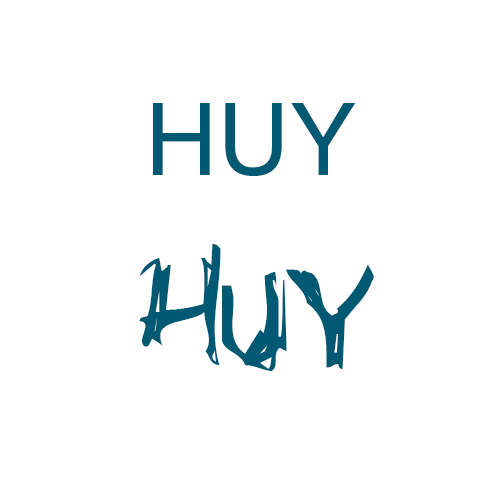
Khi bạn tạo ra một Logo hay một sản phẩm thiết kế nhận dạng thương hiệu, bạn thấy nó đẹp và sáng tạo nhưng người xem thì không thấy như vậy do nó quá phức tạp. Nói tóm lại, bạn phải chọn Font chữ thật đơn giản, dễ đọc. Nếu bạn chọn những Font chữ uốn lượn, rườm rà thì sẽ gây khó chịu cho người xem.
Bạn phải làm sao cho người xem có thể nắm được tên, màu sắc và cảm nhận được thông điệp ngay từ lần đầu nhìn vào Logo của bạn. Bạn nên chú ý về Font và cỡ chữ. Nếu như có thể bạn hãy đều chỉnh hệ chữ Bold, Regular, Light tùy ý để tạo sự sống động mà không gây khó nhìn cho người xem.
2.Khoảng cách từ và chữ
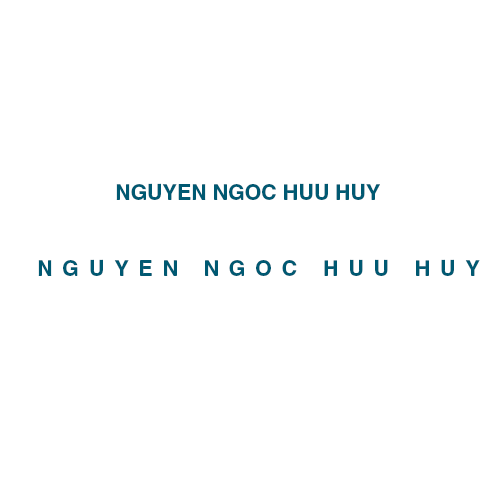
3.Phù hợp với không gian xuất hiện
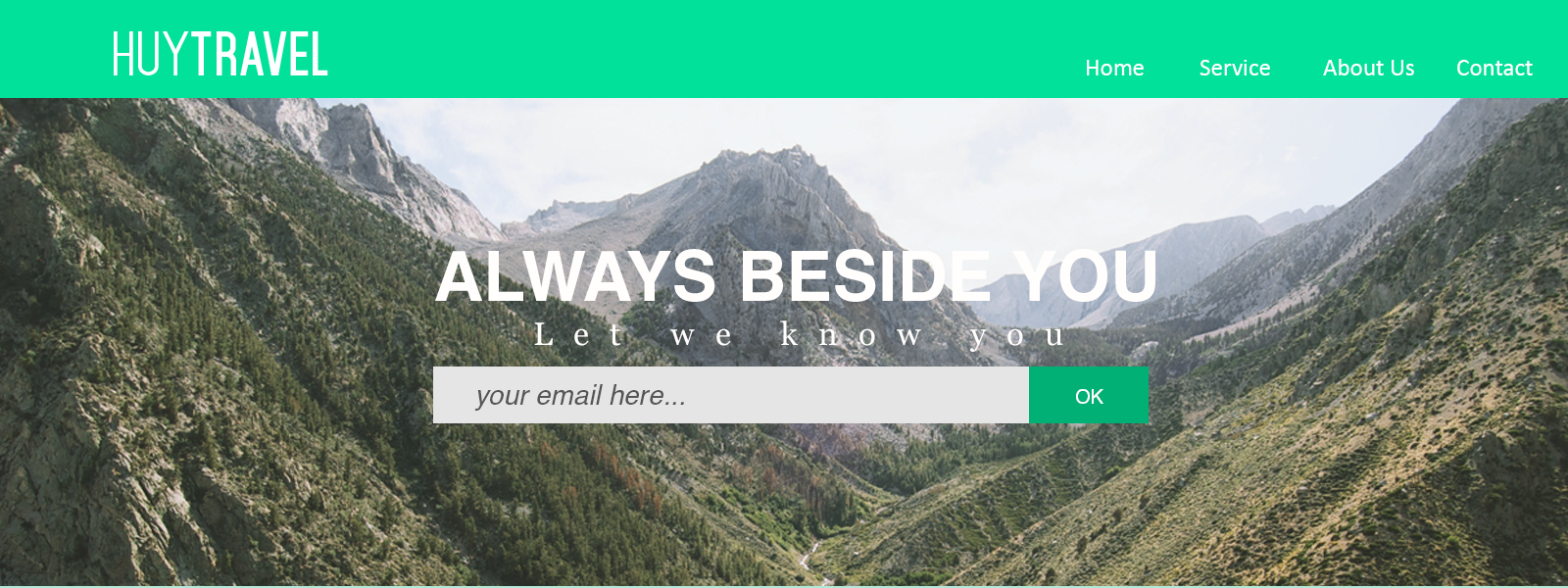
4. Thiết lập những bộ Font chữ tương thích với nhau
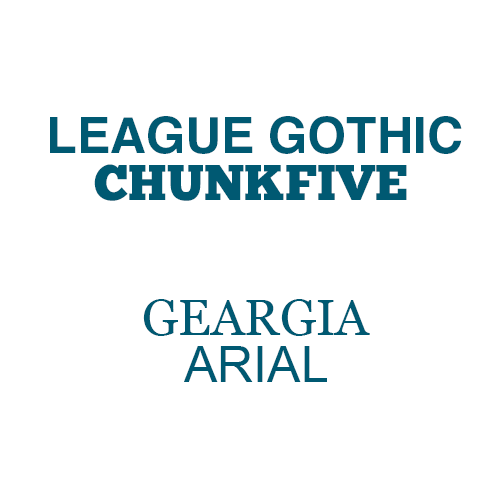
5.Nâng cao tính giao tiếp